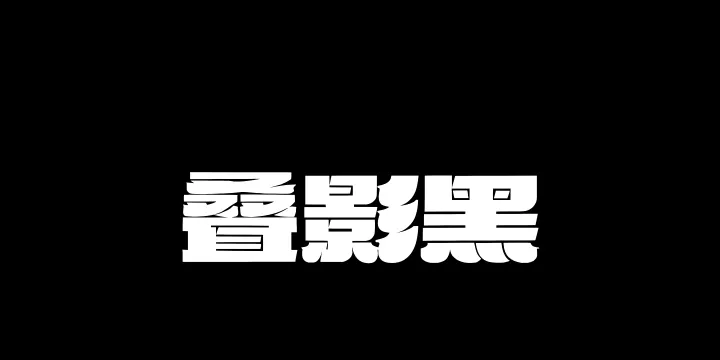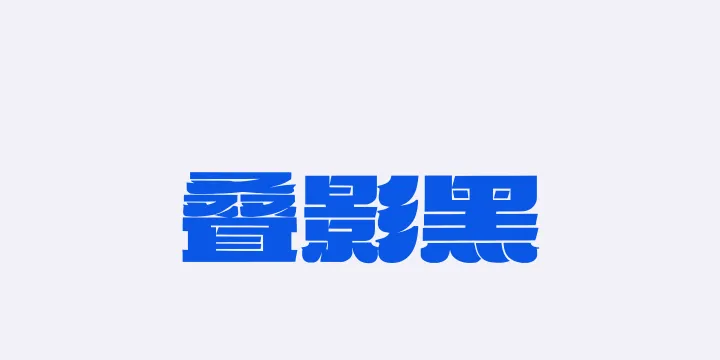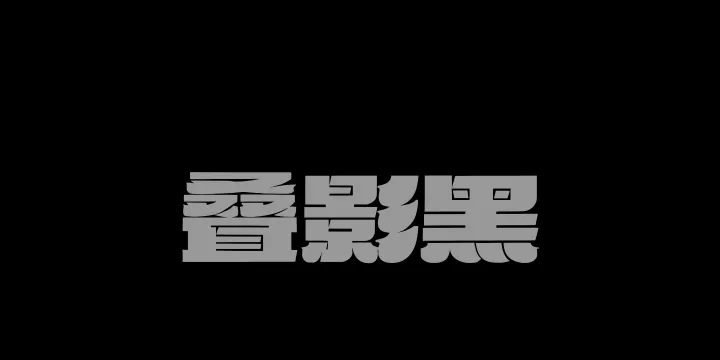
字体全名: Aa叠影黑
字体简介: 设计的点睛之笔在于笔画间的前后叠加感,部分主笔做底层加粗,辅笔以轻微偏移的方式叠压其上,形成错落的层次,既强化了字体的立体感,又避免了超粗笔画带来的臃肿沉闷。整体风格硬朗厚重却不失细节巧思,字体重心稳固、视觉张力十足,适配品牌主视觉、海报标题等需要快速抓住眼球的设计场景。
所属分类: 粗黑黑体